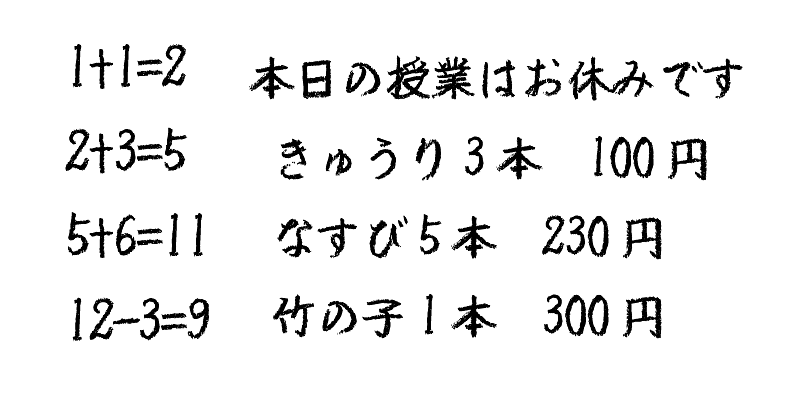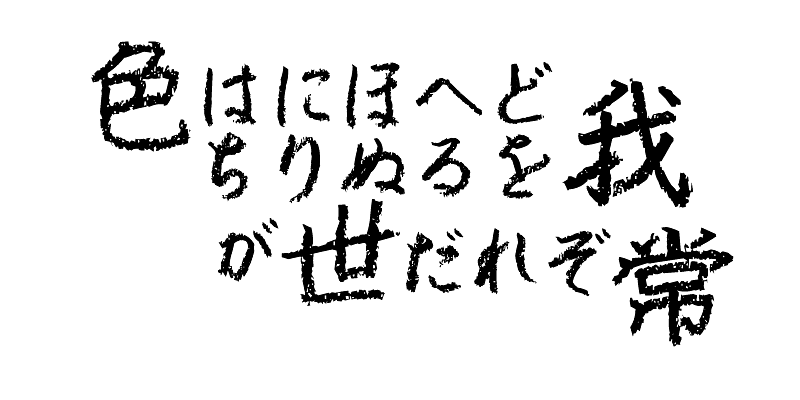
Cette typographie représente une écriture ancienne à la craie.
Cette police comprend les 1 000 principaux caractères kanji choisis dans les tables de fréquence des caractères établis par les sociétés de presse, les maisons d’édition et les instituts de recherche linguistique, ainsi que 206 caractères kana et signes de ponctuation.
Cette série de polices contient des polices japonaises originales écrites à la main basées sur la calligraphie au stylo publiées en 2002. Avec leur look chaleureux, ces polices attireront l’œil du lecteur sur les points clés d’un design.